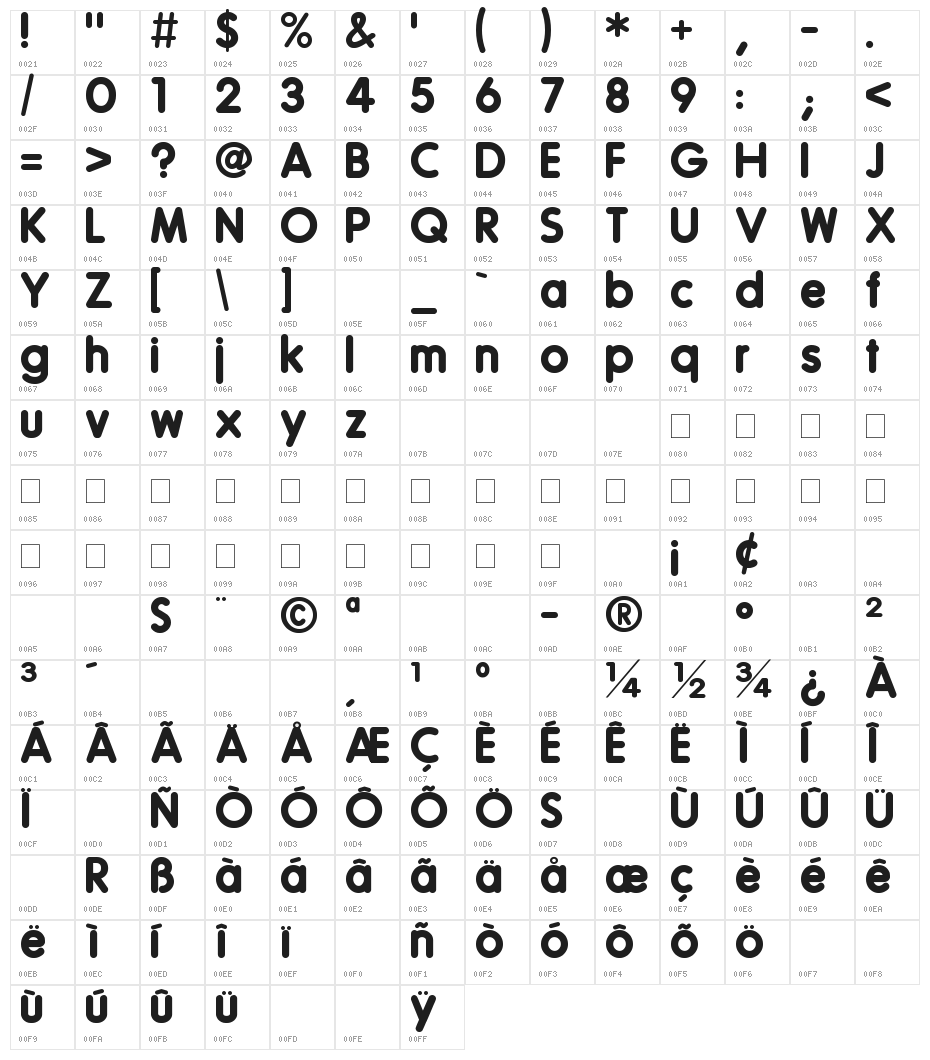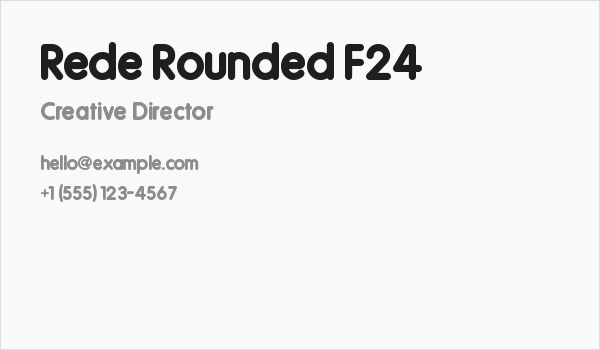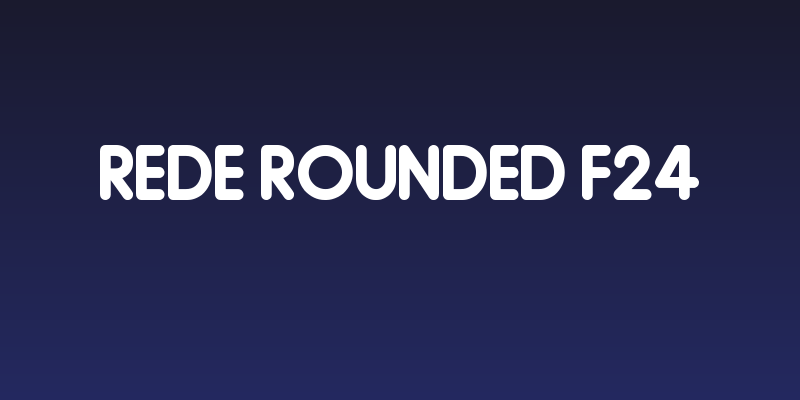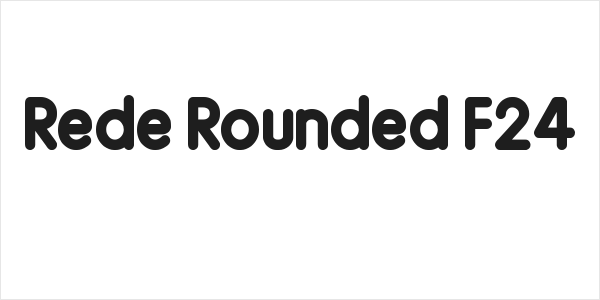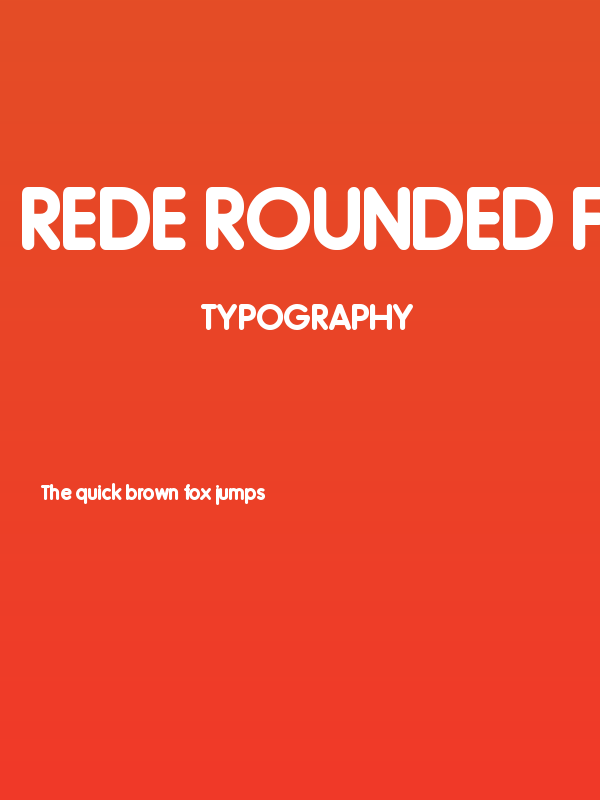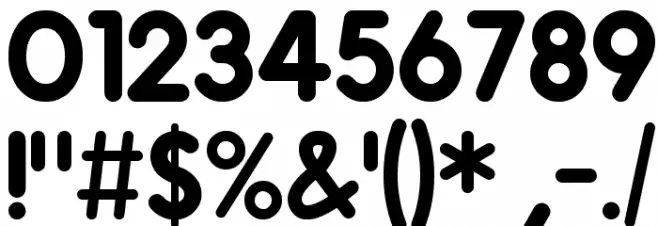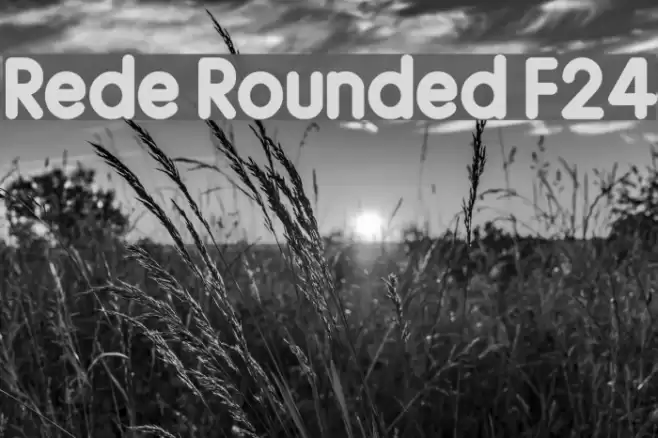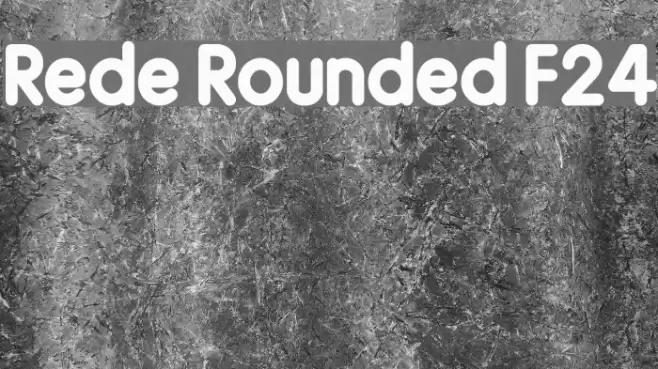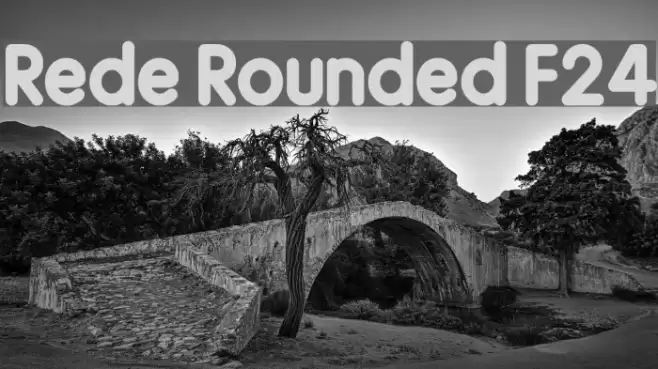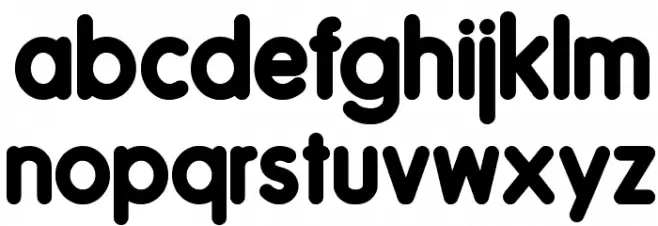
Rede Rounded F24 Font
| Caso de uso | Logos, Headlines, Branding |
| Proyectos propuestos | Ideal for branding, packaging, children's books, and digital interfaces that require a welcoming and modern touch. |